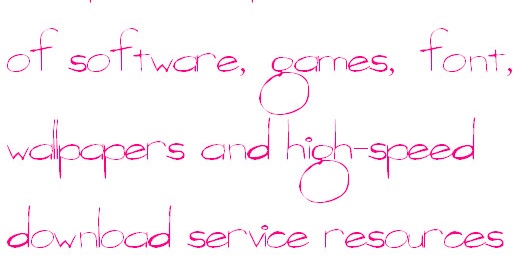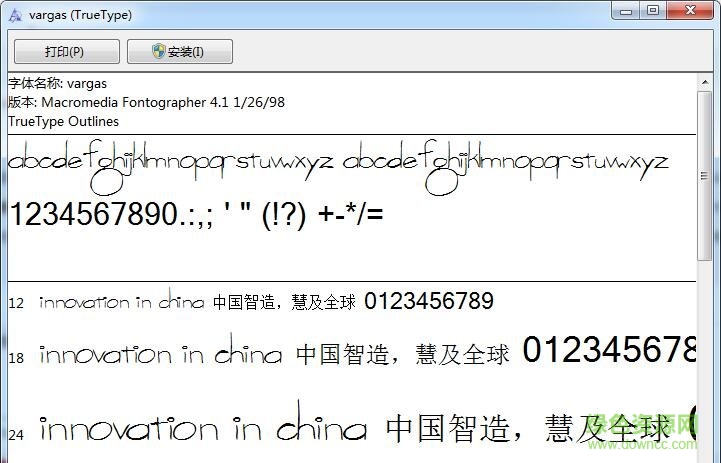
可愛卡通vargas字體很受廣大網(wǎng)友們的喜愛!這款字體在多個領(lǐng)取很受用哦!使用它輸入的字體非??ㄍɑ?,多用來設(shè)計卡通系列的作品!需要的用戶可以來本站免費下載使用!
vargas字體是一款非常可愛的卡通字體,用來卡通方面的設(shè)計非常適用。歡迎網(wǎng)友們來綠色資源網(wǎng)下載安裝。